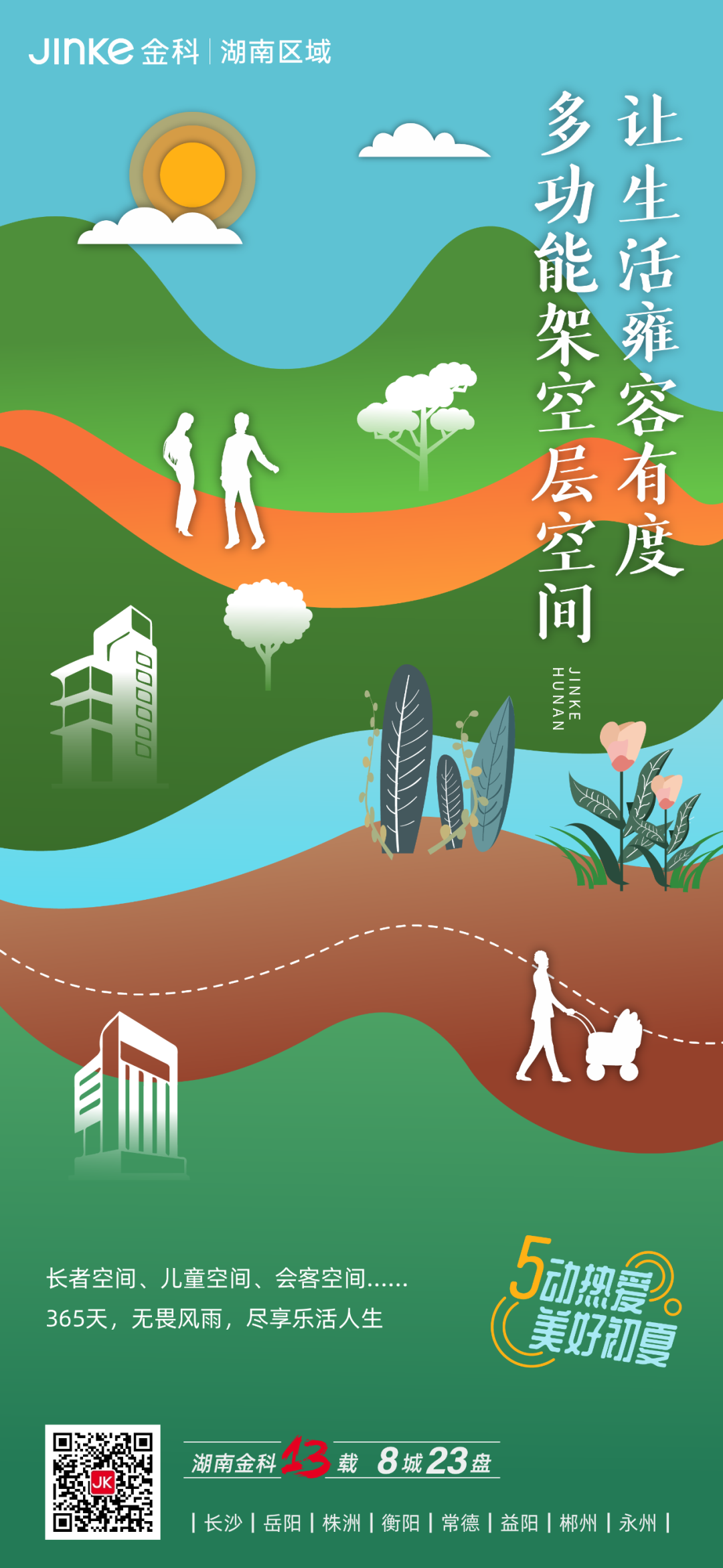
方正高原明朝体家族
方正高原明朝体是一款以作者母亲名字命名的字体,字形基于宋体经典且优雅的结构设计而成,减少了宋体具有相对锋芒修饰感的字脚,笔画圆润工整,韵律节奏恰如其分,构建出一款字形修⻓、匀称、雅韵,极具干练⻛华之气质美感的家族字体。 此款字体适合时尚、医美、化妆品类行业广告用字及画报杂志标题。
23年后,这款献给母亲的字体终于发布!
复古黑框眼镜,酷炫手臂刺青,微笑中带着几分邪魅。你以为他是个rapper?      NO!
其实是个内敛沉静、风格日式的设计师。他是“弹簧”,原名刘锡江。
不期而遇的设计人生
对于弹簧而言,设计更多是一种不期而遇,从灵感到成型,从实习到创业,都是一场不期而遇的美丽。
油画专业毕业的他,并没有系统地学习过设计。毕业后在一家广告公司实习,开始接触一些平面类软件和初级的设计工作。2003年,弹簧设计的⼀项作品获得了四川省一个广告大赛银奖,这给当时年纪轻轻的他莫大的信心,便独自一人前往成都。这看似冲动又单纯的决定,却成为他在这里发展最好的契机。实习、合作、创业、创立自己的品牌,他开始邂逅于人生中不同阶段的自己。
不期而遇,尽在偶遇,是无法预料,是不可避免,是用力生活后的随遇而安。如同每一次悄然而至的身份转变,方正高原明朝体的出现也是一场不期而遇。
这套字体的原型是弹簧为成都品牌设计俱乐部所做的一套标准字,在一次活动上有幸得到古田路林老师的引荐,认识了方正字库的海朝老师。历时3年多时间,与方正字库合作设计师郭炳权老师共同设计和完成了这套字体的开发。
以母亲之名再现字体之美
这款字体的命名则是弹簧为了纪念他的母亲——高原。她是一位身材高挑,知书达理并有具有超强人格魅力的女性。1997年,母亲因病离开,对于当时还是懵懂少年的弹簧来说,无疑是沉重的打击。而母亲身上的善良、坚韧的性格,一直深深地影响着他的成长。成年之后,在自己的专业领域也取得过一些小小的成就,但非常遗憾不能再与她分享。以母亲之名,设计一款字体,或许可以永世流传,他想用这种方式表达对母亲无尽的思恋。
宋体是在我国明朝形成的一种专门用于印刷的字体。这套字体基于宋体字结构设计而成,形态端庄、简约大方,经典且优雅。睹字思人,看到这款字,弹簧仿若看见了母亲端庄娴雅的身影。
同时,字体减少了宋体笔画中相对锋芒、修饰感的字脚,去掉显性的外在表现,突出字体本身的气质,美而不张扬。如同弹簧对母亲的爱,含蓄而深沉。笔画圆润工整,轻柔流畅,部分笔画断开,空间留白,结构上呈现出“放松”的状态。
点画如欲滴之露,柔美而略带俏皮,具有向下坠落的动感;钩画状如鸟头,下部重顿,有一种静态的自然美感。
整套字体字面偏窄,重心偏高,中宫偏小,构建出一款字形修长挺拔、匀称雅韵,极具干练风华之气质美感的家族字体。设计时,弹簧将母亲身材高桃的形象勾勒进笔画中,透过字体充分展示了女性高挑曲线的魅力。
值得一提的是,方正字库合作设计师郭炳权团队基于中文字形设计了气质吻合的西文字体。
方正高原明朝体家族一共有6款字重,整个字体设计工作从2017年5月开始,在设计过程中获得高兴机构大桥、晓宇、一枪、王帅等同学的诸多帮助。
2018年,洪晃老师的“时尚悬念爱情侦探小说”——《张大小姐》一书的封面,使用了这款还在创作过程中的字体,并获得了广泛好评。
应用展示
方正高原明朝体适合时尚、医美、食品、化妆品类行业广告用字及画报杂志标题。在版式用字中竖排则更具雅韵气质。